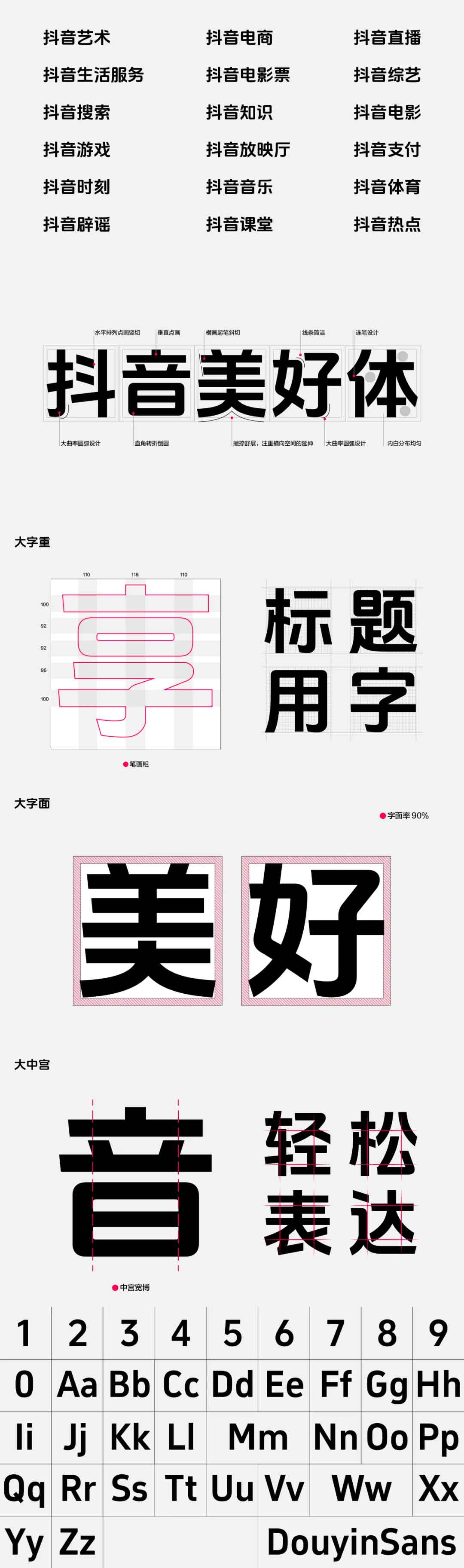
抖音美好体
字体简介
设计理念:以 “年轻化、视觉友好、动态适配” 为核心设计理念,专为短视频、直播、社交媒体等场景优化,旨在提升移动端内容的可读性与表现力。
字符集:包含 6763 个中文字符和 682 个西文及数字符号,执行国家 GB2312-80 简体中文编码字符标准,同时覆盖超过 3 万个汉字,支持简体、繁体及常用日韩字符,兼容拉丁字母、俄文、泰文等多种语言。
字体特点:提取了 “抖音” logo 字体简约清新的风格特征,为适应标题场景,采用较粗的大字重字体。90% 的大字面率,呈现出美观大方、清晰易读的视觉风格。大中宫设计,使字体更加舒展饱满。笔画采用无衬线设计,末端微带弧度,字符重心略向下偏移,西文字符也经过圆角化处理,中英文搭配协调。
技术亮点:支持字重、字宽动态调节,针对 90Hz/120Hz 高刷屏幕优化,采用像素级 Hinting 技术,针对 OLED 屏幕子像素排列进行了优化,并提供了暗黑模式专用字重。此外,还基于抖音海量视频字幕数据训练模型,可自动优化字形比例,与抖音 App 深度集成,能实现字体特效实时渲染。
应用场景:广泛应用于抖音端内核心场景,如首页标题、活动 banner 等,也常用于市场传播物料,如海报、宣传片字幕等。同时,剪映、醒图等热门创作工具也内嵌了这款字体,还可用于小红书、微信视频号等跨平台内容,保持品牌视觉统一性。